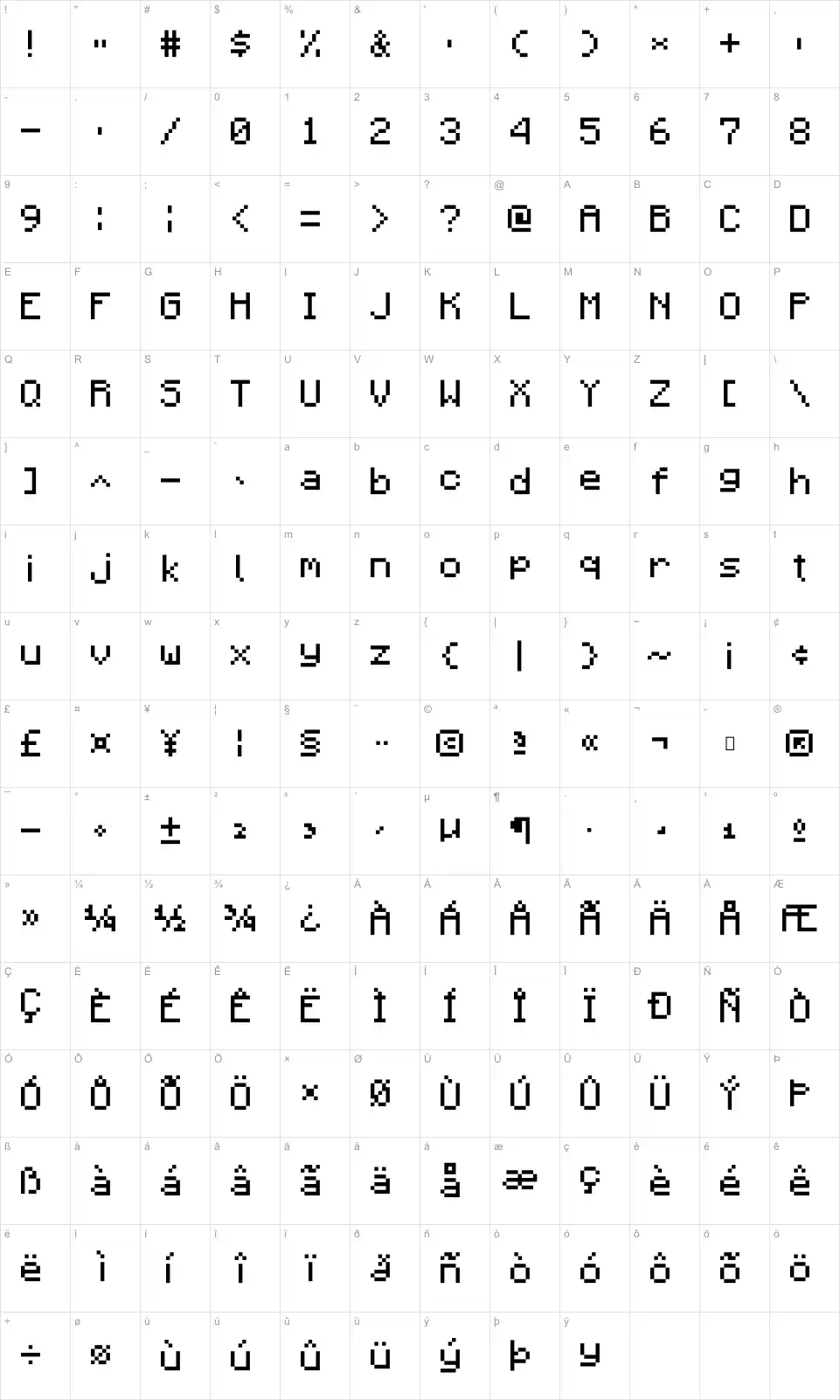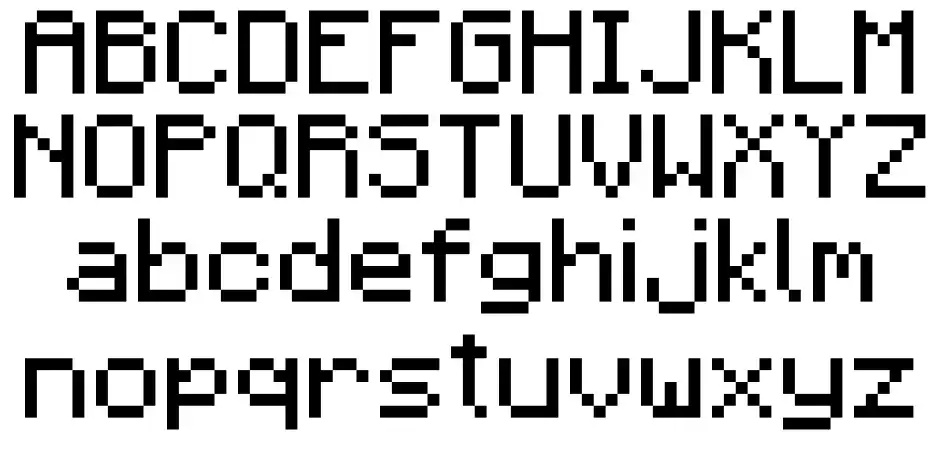
Five Fonts at Freddy’s – Fonte Grátis
Five Fonts at Freddy's
A fonte ‘Five Fonts at Freddy’s’ para a categoria Techno, criada pela equipe Five Fonts at Freddy’s, está disponível para download ou gerar uma pré-visualização personalizada de texto online. Esta fonte é uma excelente escolha para criar um design visual atraente e moderno. Licenciada em modelo demo, você pode experimentar a fonte sem comprometer a legalidade. Com formato TTF, você pode incorporá-la facilmente em seus projetos digitais. Adicionada em 11 de julho de 2022, já foram 2954 downloads desta fonte criativa. Com seu tamanho de 16 KB, é uma opção leve e eficiente para seu próximo projeto. Seja para aplicativos, sites ou impressões digitais, esta fonte Tech-avaliada certamente adicionará um toque único ao seu trabalho.